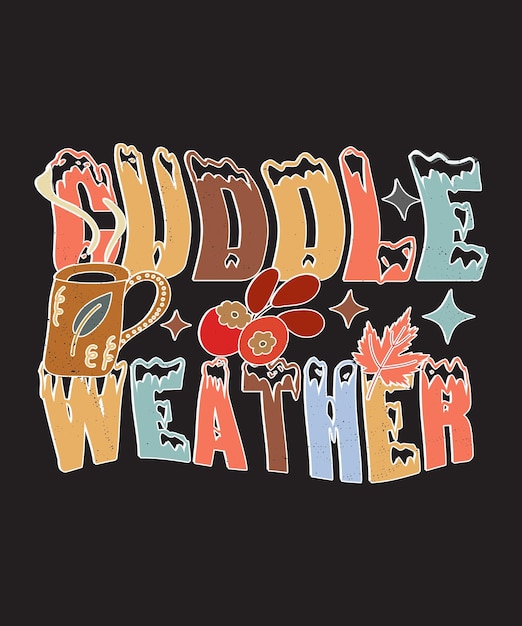
jesień i jesień napis, jesień i jesień na białym tle ręcznie rysowane groovy typografia vintage t-shirt.
Jesień i jesień napis, jesień i jesień na białym tle ręcznie rysowane groovy typografia vintage t-shirt.